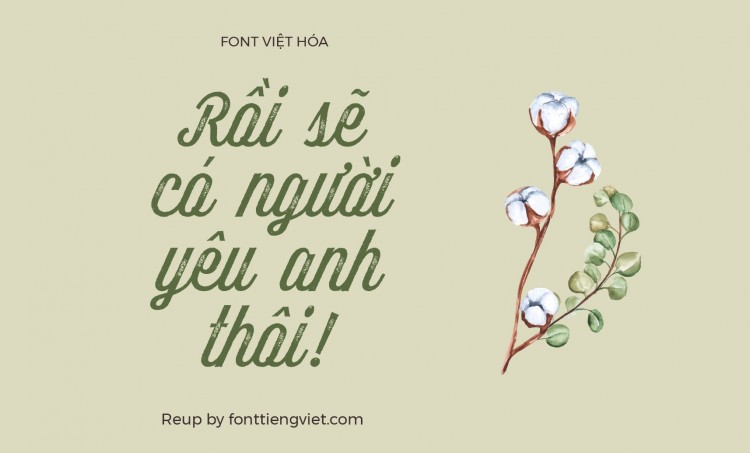
Font việt hóa MTD Authentica Rough
Trong thế giới đồ họa hiện đại, việc tìm kiếm một bộ Font việt hóa MTD Authentica Rough chất lượng là điều vô cùng cần thiết đối với các bạn học sinh và thầy cô giáo. Đây là một kiểu Font Miễn Phí mang đậm phong cách Vintage, giúp tạo nên những bài thuyết trình hay ấn phẩm truyền thông học đường đầy ấn tượng. Với những đường nét thô mộc đặc trưng, bộ font này mô phỏng chân thực kỹ thuật in ấn thủ công cũ, mang lại cảm giác hoài cổ và gần gũi cho người xem.
Đặc điểm nổi bật của Font việt hóa MTD Authentica Rough
Phong cách thiết kế độc đáo
Bộ Font việt hóa MTD Authentica Rough sở hữu những nét vẽ không hoàn hảo, tạo hiệu ứng “Rough” (nhám) rất tự nhiên. Chính sự không hoàn hảo này lại giúp các tiêu đề bài học hay bìa báo tường trở nên có hồn hơn. Font chữ này cực kỳ phù hợp cho những ai yêu thích sự phá cách nhưng vẫn giữ được vẻ trang trọng, tinh tế cần thiết trong môi trường giáo dục.
Khả năng ứng dụng đa dạng
Người dùng có thể sử dụng bộ font này cho nhiều mục đích khác nhau như làm thiệp mời, thiết kế logo câu lạc bộ, hoặc trang trí các bảng tin lớp học. Nhờ quá trình việt hóa kỹ lưỡng bởi MTD, các bạn không còn lo lắng về lỗi hiển thị dấu tiếng Việt, giúp văn bản luôn mượt mà và chuyên nghiệp trên mọi phần mềm đồ họa phổ biến hiện nay.
Hướng dẫn sử dụng và kết luận